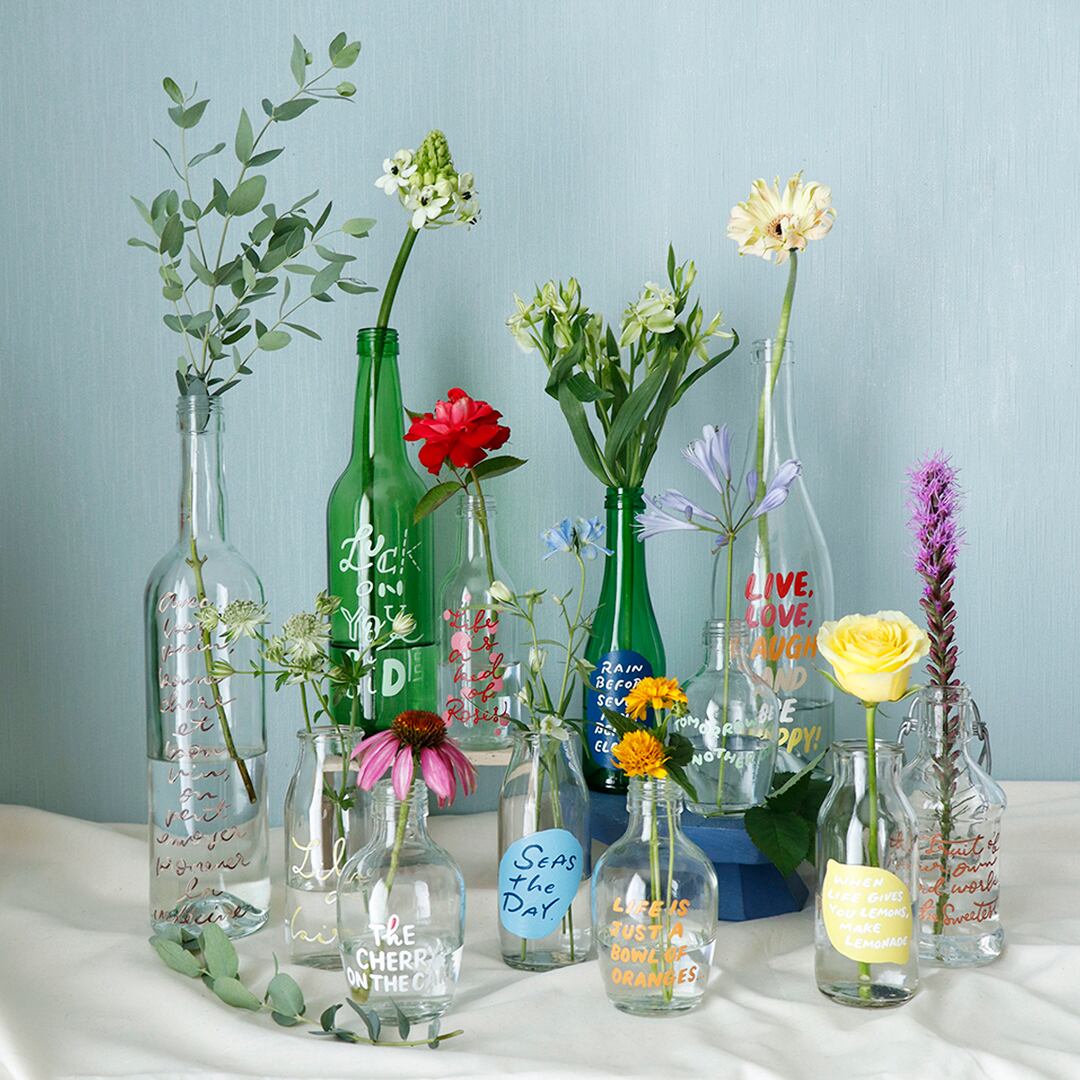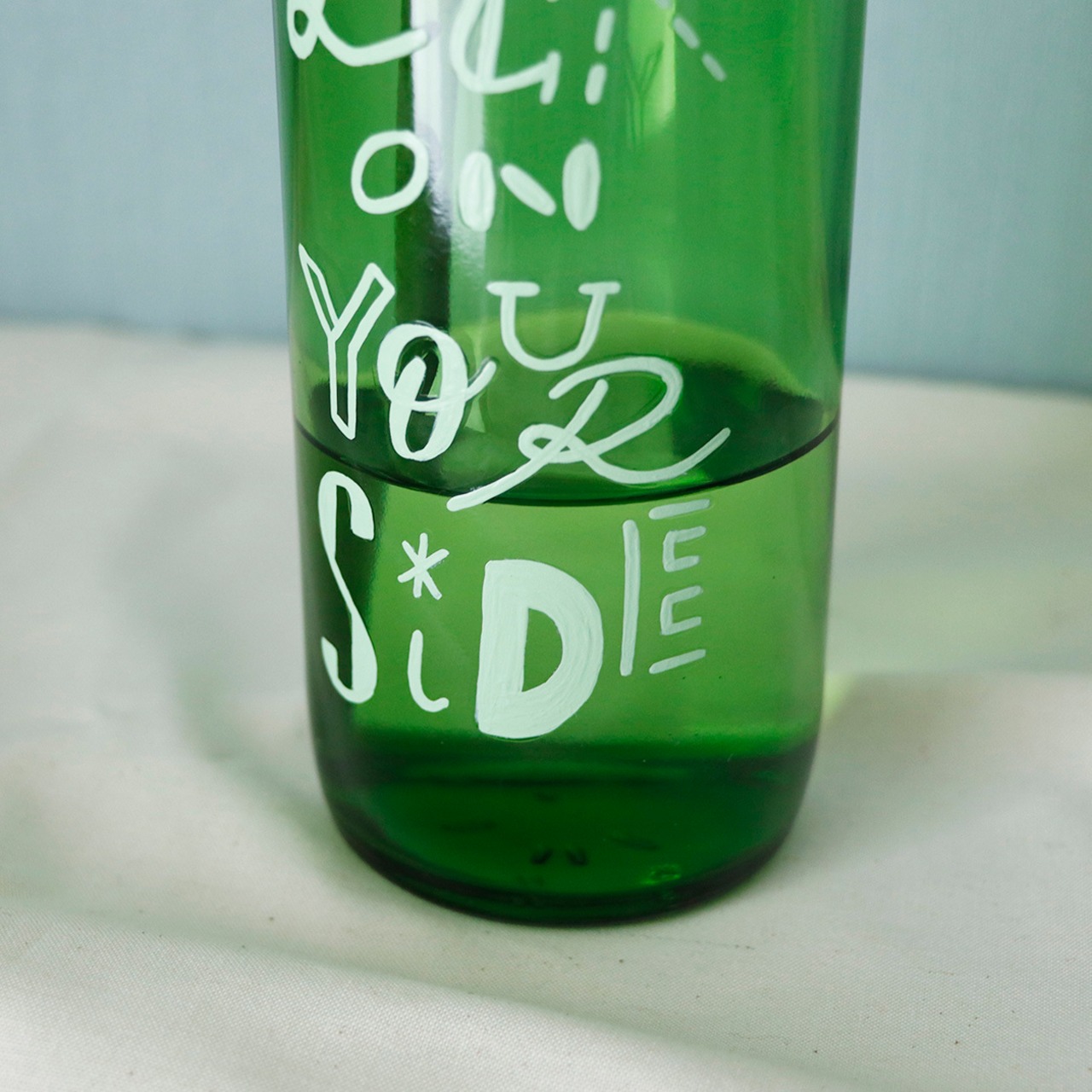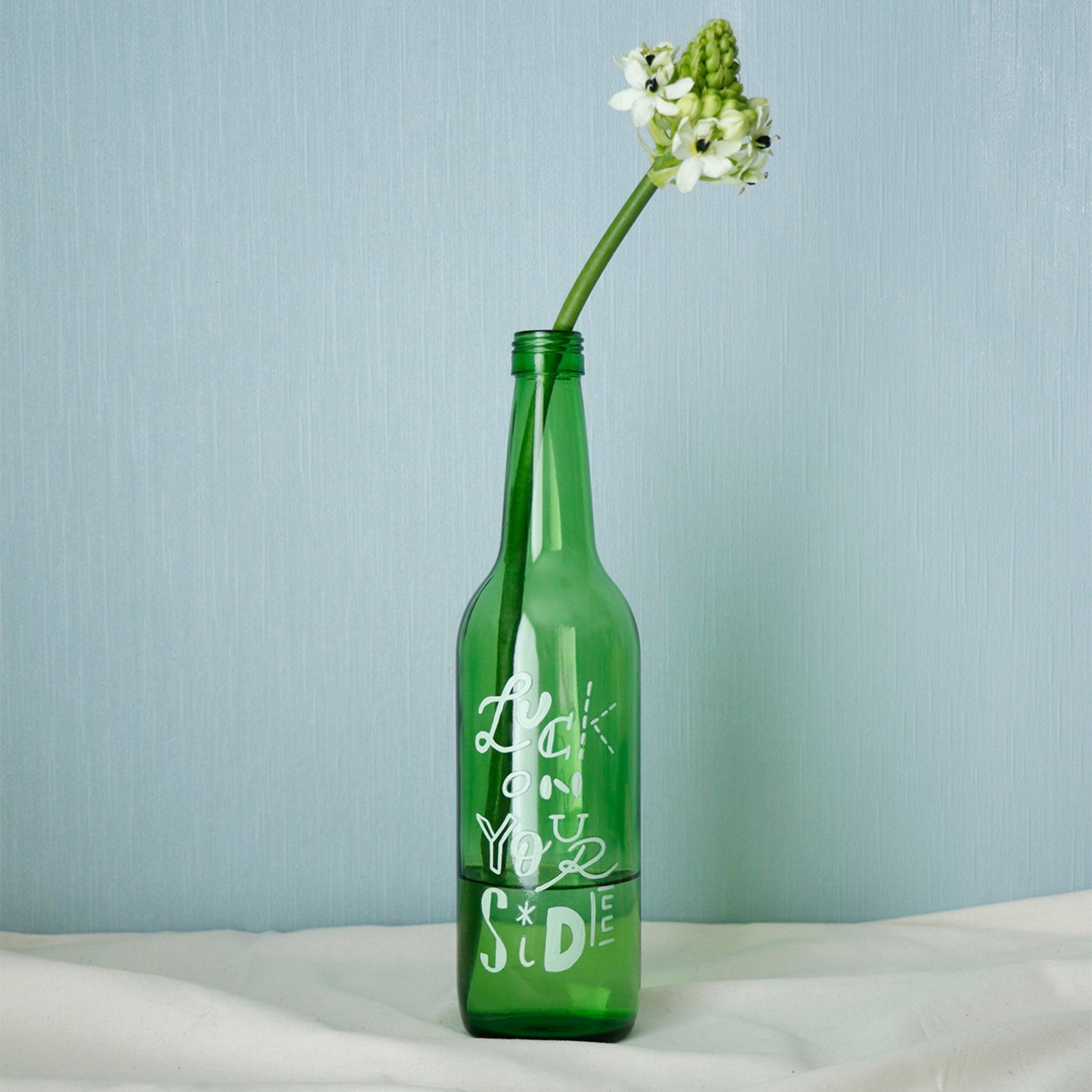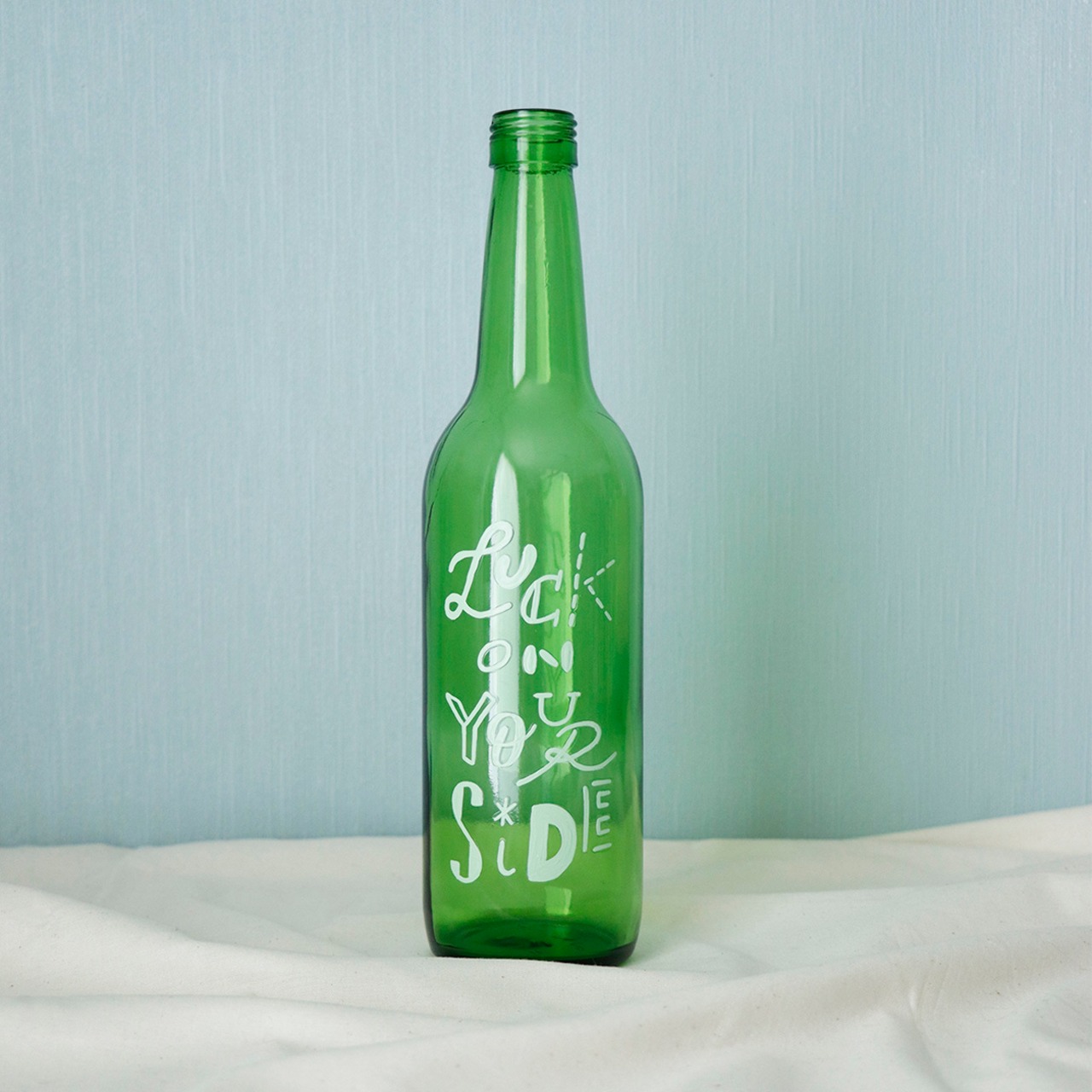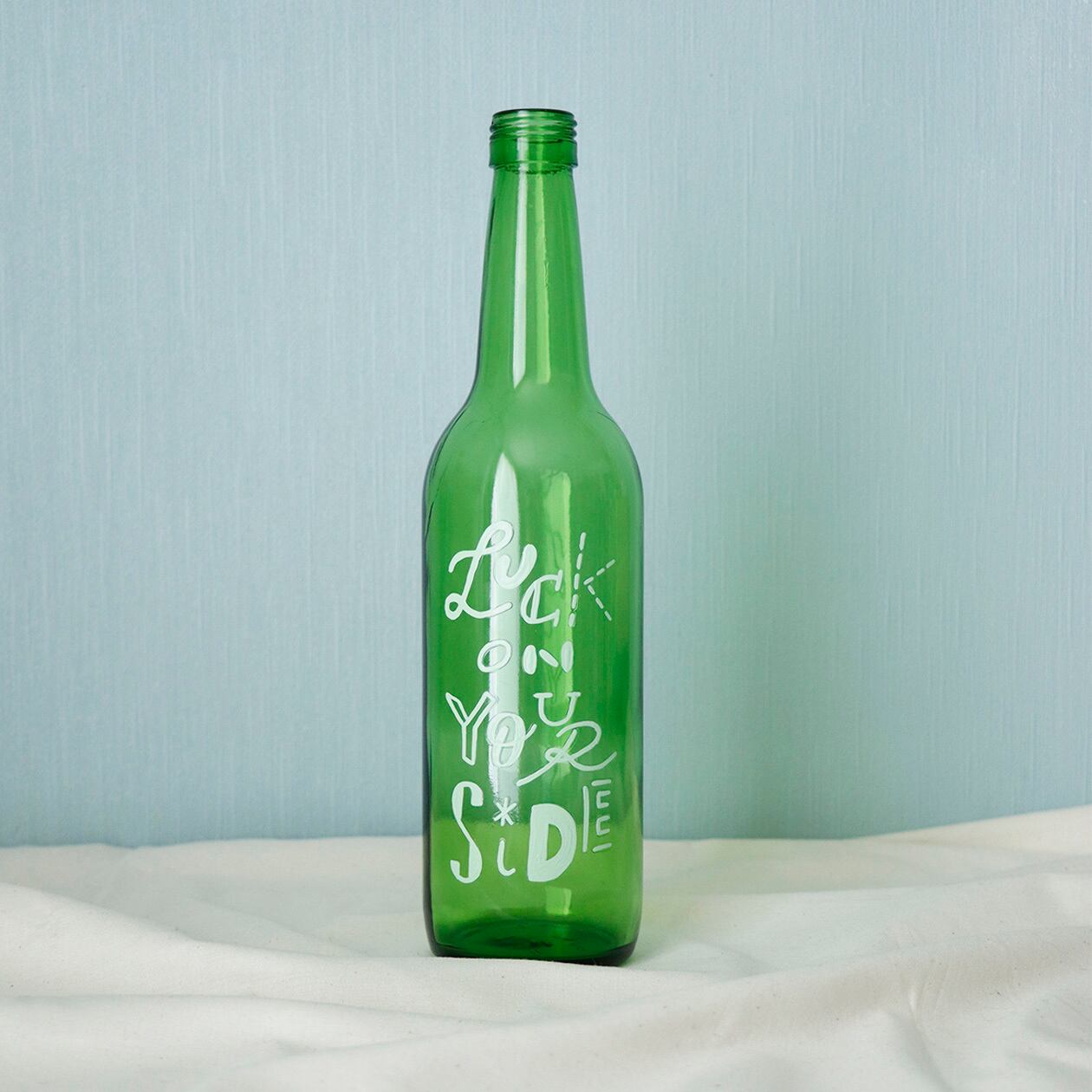
【BOTTLE PAINT ART】Luck on your side 03
Luck on your side
幸運が味方してくれてる!
全部異なるフォントで描いています。
ボトルではなかなか描かないデザイン。
ちょっと変わったお花が断然似合う!!
光が入るとこに置くと、瓶の色とともに文字も影になって素敵ですよ!!